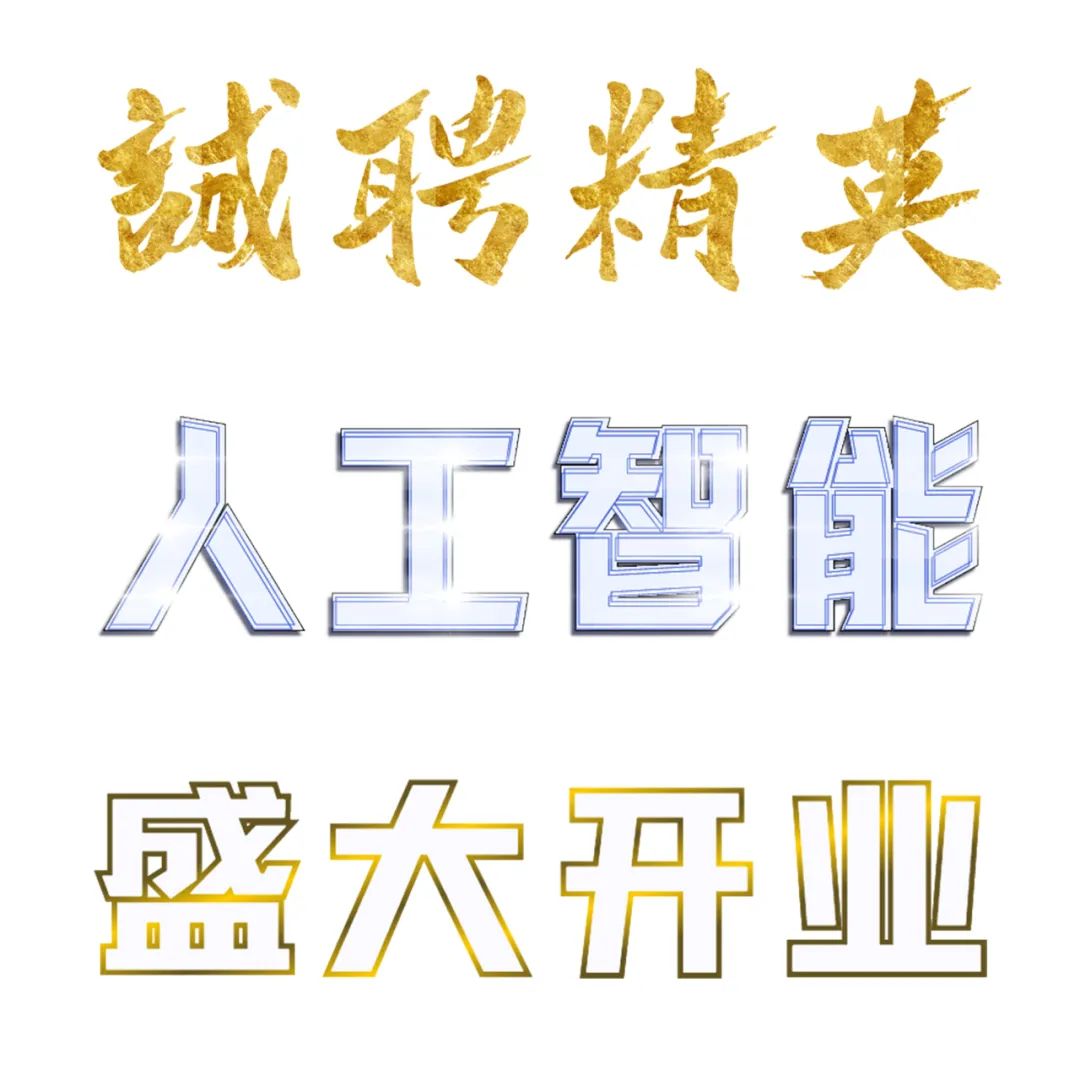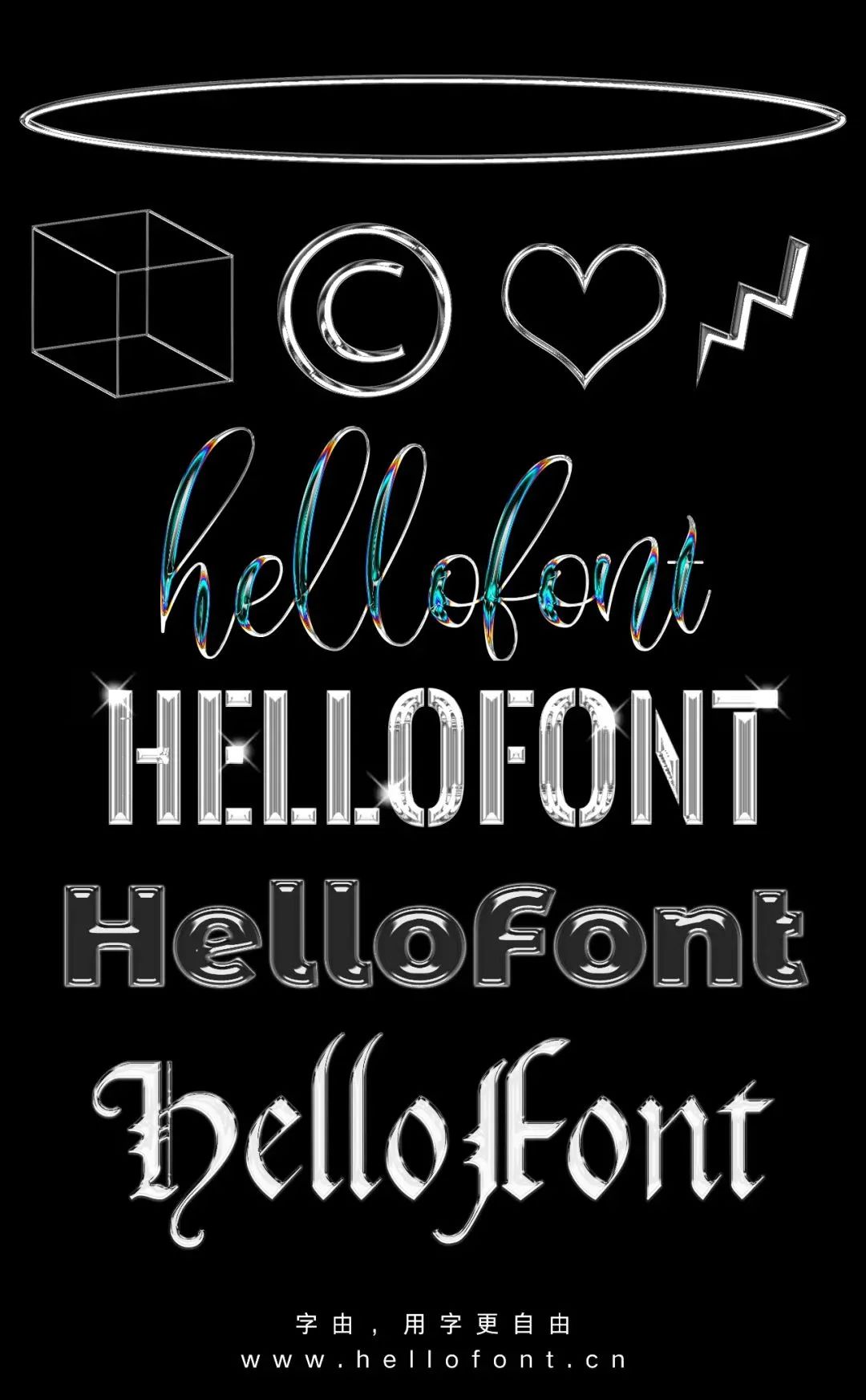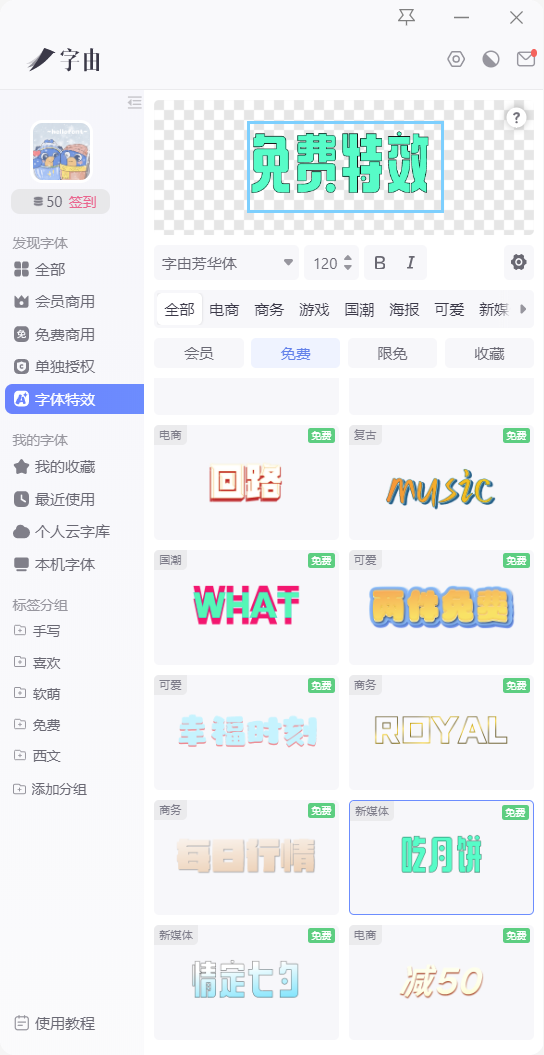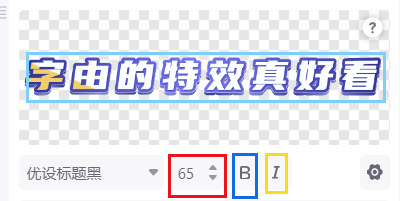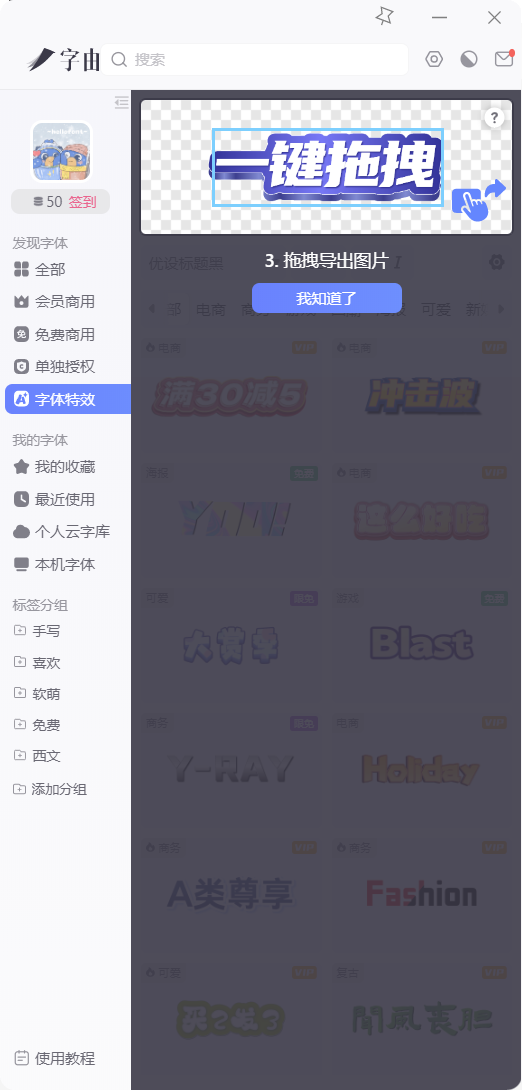
卷大神,救小白,这个字体特效,主打的就是一个省时省力!
今天柚子要来考古了,不知你们还记不记得N久以前的字体特效。
emmm,可以但没有必要,主要是有点low,有点报看(大胆开麦,勇敢吐槽)~
以至于后面把这个入口隐藏了,还有用户过来询问,怎么找(这是有多懒得做特效)?
一方面感谢你们容忍度这么高,一方面也觉得字体特效确实是刚需,不仅针对刚入门的小白,哪怕是有经验的设计师, 也希望能省去在特效方面投入的时间精力,提高做图效率,不然怎么那么多人喜欢套模板,现成的还是香!
多种场景的字效
所谓不破不立,这次字由推出了全新的字体特效(up了不止一个档次),首批上线203款(后续还会不断更新),特意匹配了不同使用场景,不管是电商需要的氛围感:
还是广告需要的贵气感:
亦或是Z世代追求的个性感,特效都能满足你~
说到这里,你一定心动了,那接下来柚子就教你怎么炫在软件上。
自定义特效功能
然后就可以在界面左边看到字体特效。
选一个喜欢的,然后在顶端编辑文案,这里双击是全部替换(也可以ctrl+c,ctrl+v文案),单击可以加字、减字,但是不能超过十个字,也不可以换行哦~
如果你觉得这个特效还差点意思,可以在设置里调整,比如文字可以调颜色,贴图。
还可以调字间距、特效强度、大小等。
当然字号、加粗、 斜体,这些细节也要有。
背景不好看,也可以调,不管是关闭眼睛,还是增减描边、投影,玩的就是个性化。
在不改变字体的情况下,可以变出N多样式。
当然,也不用担心调过头了,随便点一个别的特效,再点这个就还原了。
客户端一键拖拽
编辑好了字体特效,怎么导出,这是很多人关心的问题。
其实超级简单,就是直接拖到软件里,是PNG的格式。
看我给你演示一下~
只要你编辑好文案,就可以直接拖你喜欢的特效,改字体也不成问题。
虽然现在特效还没那么多,但随着以后越来越多,相信我,你会需要一个收藏的,点击特效右下角的小星星,就可以在收藏里找到啦~